優美で洗練されたデザインや、遊び心のある手書き風デザインで活躍するのが、英字の筆記体(スクリプト)フォントです。ロゴやタイトル、装飾的なワンポイントに使うと、一気に雰囲気が出ます。
この記事では、デザインのアクセントに使える英字の筆記体フォントを33種類紹介します。結婚式の招待状や、年賀状の「Happy New Year」といった文字デザインにも使えるので、用途に合わせて選んでみてください。フリーフォントから有料フォントまで含まれています。
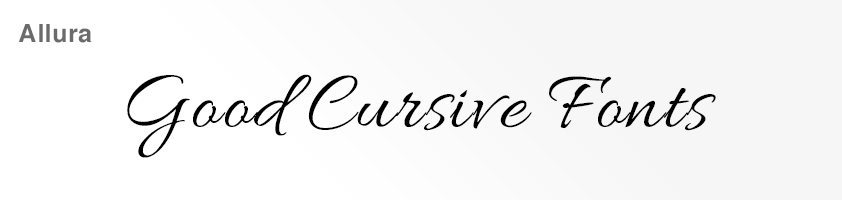
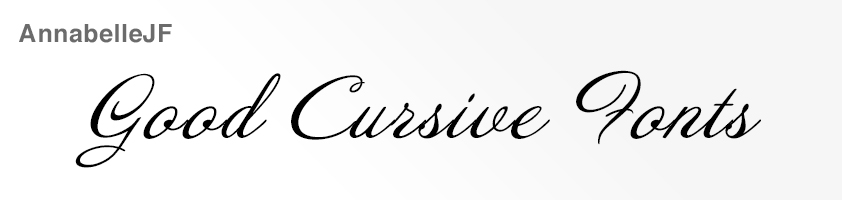
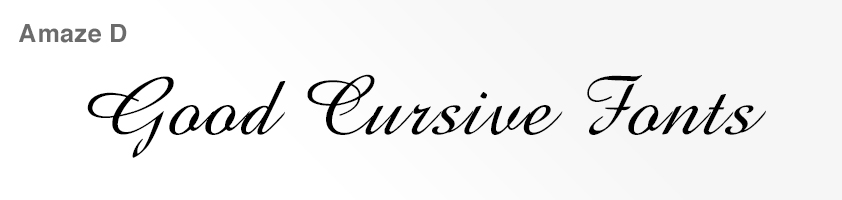
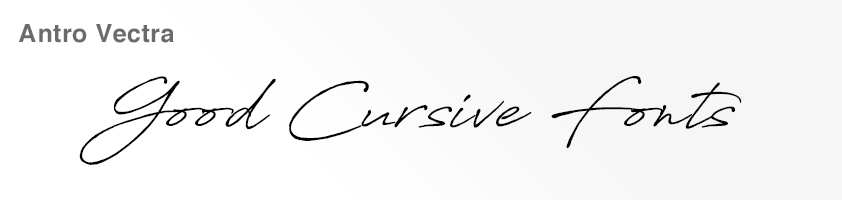
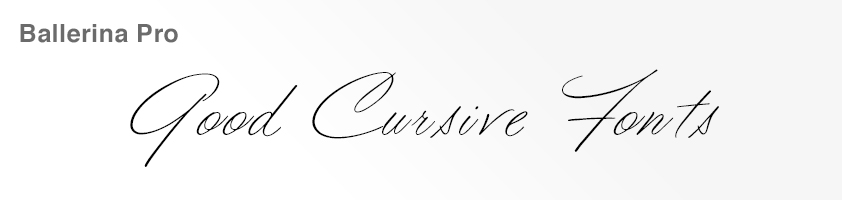
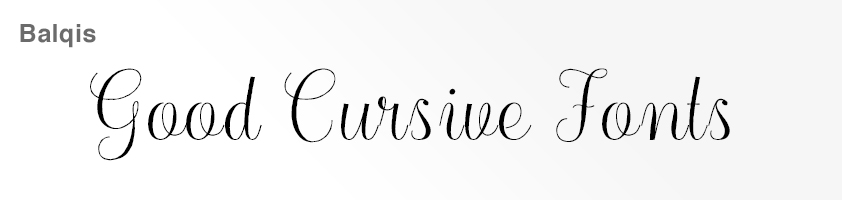
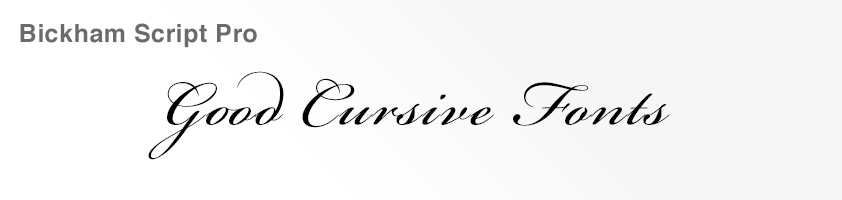
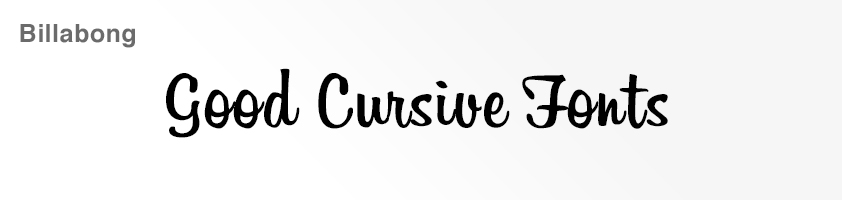
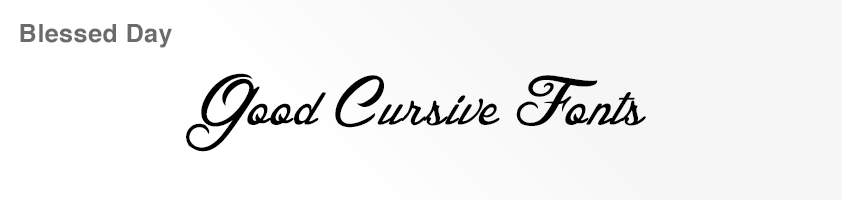
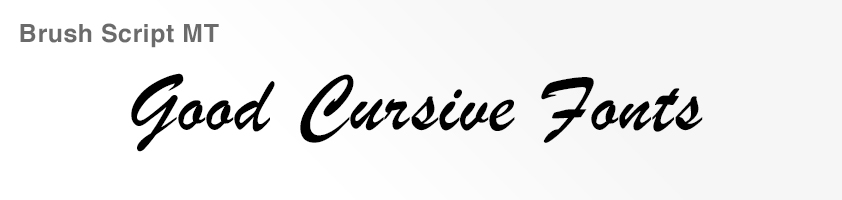
筆記体フォントは、ロゴやタイトル、装飾などデザインのアクセントとして使用するには効果的ですが、一般的には可読性が低い場合が多いです。
定番フォント(可読性の高いフォント)と合わせて使用することで、読みやすさを保持しつつ印象的なデザインを作ることができます。
筆記体フォントは装飾性が高いぶん、長い文章や小さいサイズでは読みにくくなります。見出しやワンポイントなど、短い英字に絞って使うのがおすすめです。